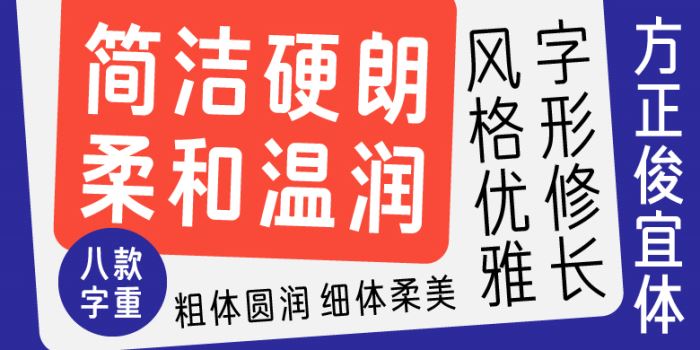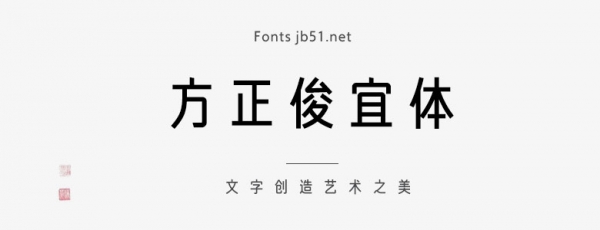
方正俊宜體家族由方正字庫崔艷設(shè)計(jì)師出品的藝術(shù)字體,字體保留了俊黑體字形修長、風(fēng)格優(yōu)雅的特征。將筆畫轉(zhuǎn)折處做圓角處理,相較于俊黑體的簡潔硬朗,適合應(yīng)用于藝術(shù)設(shè)計(jì)、平面宣傳設(shè)計(jì)、網(wǎng)頁設(shè)計(jì),書法等領(lǐng)域。
俊宜體家族是在方正俊黑家族基礎(chǔ)上設(shè)計(jì)的,保留了俊黑體字形修長、風(fēng)格優(yōu)雅的特征。將筆畫轉(zhuǎn)折處做圓角處理,相較于俊黑體的簡潔硬朗,俊宜體更顯柔和溫潤,親和感強(qiáng)。方正俊宜體家族共有8款不同字重,粗體圓潤飽滿、圓角特征明顯,細(xì)體優(yōu)雅柔美,是一套適用型強(qiáng)的家族字體,可應(yīng)用于廣告標(biāo)語、包裝設(shè)計(jì)、書刊出版、屏幕顯示等。。